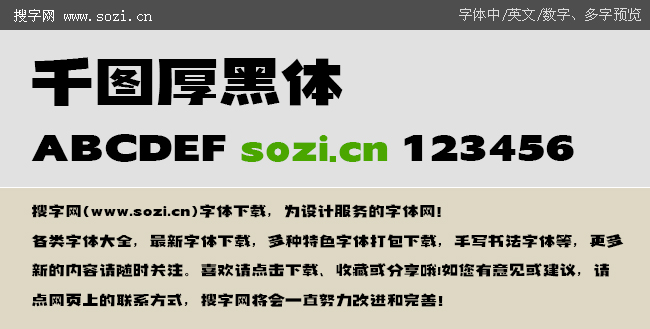
千圖厚黑體
搜字網(wǎng)給大家提供一款千圖厚黑體(非商業(yè)使用)中文字體下載,該字體是一款藝術(shù)字體,字形筆畫(huà)粗獷有力,用寬扁型的字面構(gòu)建出厚重的字體形態(tài),筆畫(huà)細(xì)節(jié)上的修飾既增強(qiáng)了字體的設(shè)計(jì)感,又讓字體多了一些小小的精致感,中宮的飽滿(mǎn)使得文字之間的排版組合非常醒目好看。適用于海報(bào)設(shè)計(jì) 、書(shū)籍封面、包裝設(shè)計(jì)等場(chǎng)景。